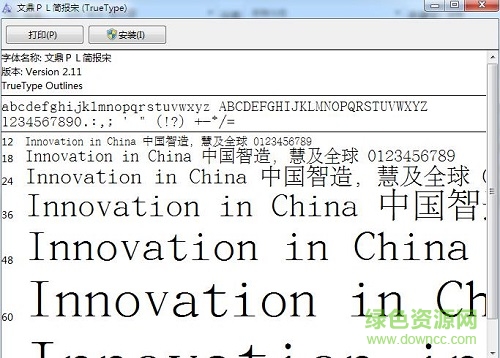
文鼎簡(jiǎn)報(bào)宋是一款專為需要用到各類字體的朋友準(zhǔn)備的中文字體,這款字體不僅延續(xù)宋體字體的一切精髓,還進(jìn)行了一定的創(chuàng)新,感興趣歡迎下載使用!
文鼎簡(jiǎn)報(bào)宋是一款由漢鼎制作的簡(jiǎn)體宋體字體,這個(gè)字體字形清秀大方,華而不浮,非常適合廣告設(shè)計(jì)、平面設(shè)計(jì)、印刷包裝、正文標(biāo)題等人員使用。